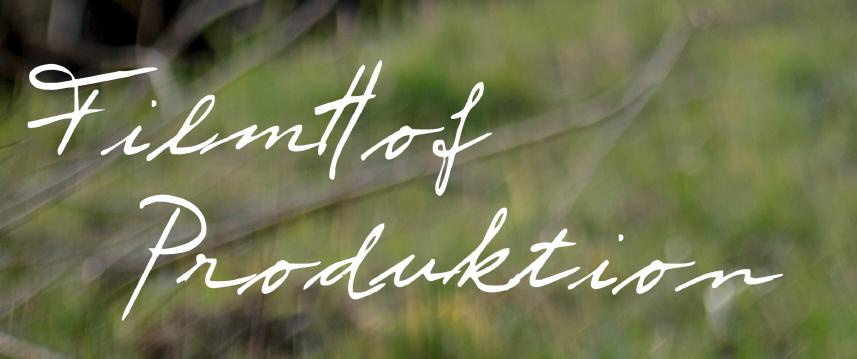
ich suche die Schriftart, die für die Bildsignatur auf dem Bild im Anhang genutzt wurde. Suchen bei WhatTheFont und WhatFontIs erbrachten keinen Erfolg.
Aber das ist schon schlimm, oder? Die Ansätze stimmen gar nicht, da findest Du bestimmt Besseres.